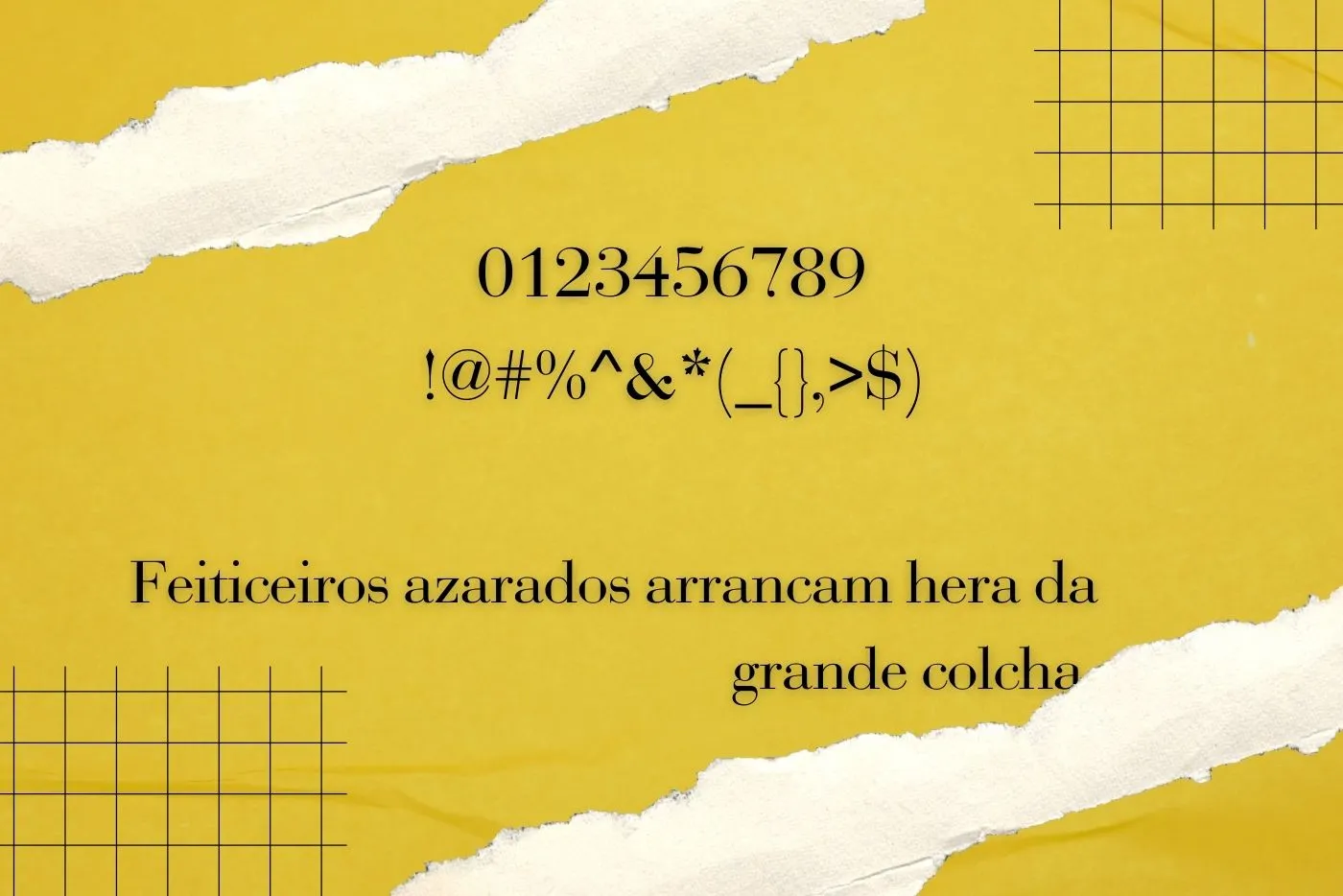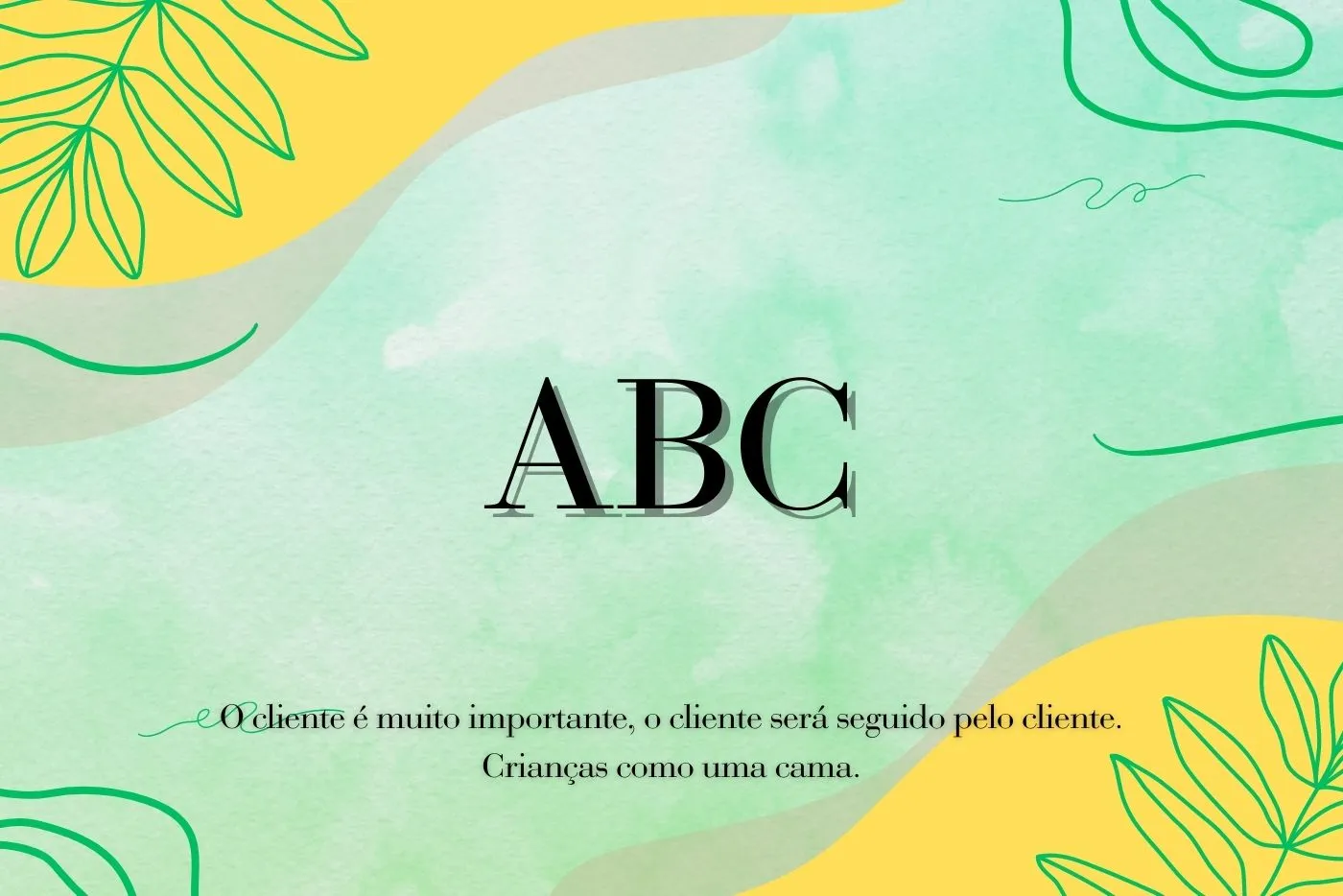
A fonte Bodoni é uma fonte serifada criada pelo designer italiano Giambattista Bodoni no final do século XVIII. A fonte é caracterizada por seu alto contraste entre linhas finas e grossas e suas serifas elegantes e nítidas.
Bodoni é amplamente considerado um dos designers de tipos mais importantes do século 18, e seu tipo de letra é frequentemente usado em design gráfico e impressão. Seu semelhante fonte liberty é muito clássico.
Bodoni criou vários estilos de sua fonte, incluindo Bodoni Antiqua, Bodoni Bold e Bodoni Ultra. Cada estilo tem suas próprias características únicas, como espessura do traço e espaçamento entre letras. Essa fonte é frequentemente usada em design editorial, especialmente para títulos e cabeçalhos. Você também pode verificar a ferramenta geradora deste tipo de letra para vários designs.
Você também pode verificar a ferramenta geradora online desta família de fontes. Essa fonte contém um grande número de caracteres e glifos, incluindo letras maiúsculas e minúsculas, números e sinais de pontuação. A fonte é frequentemente associada à elegância e sofisticação e é popular no design gráfico de luxo.
Fonte Bodoni História
A história desta fonte começa no final do século 18, quando o impressor e tipógrafo italiano Giambattista Bodoni a projetou. Bodoni foi um dos impressores mais célebres de sua época e é amplamente considerado um dos maiores tipógrafos de todos os tempos. Ele era conhecido por sua habilidade em criar tipos de letra elegantes e precisos, com proporções perfeitas e letras requintadas.
Bodoni desenhou a fonte que leva seu nome em 1798, depois de trabalhar por muitos anos como impressor em Parma, na Itália. Seu objetivo era criar uma fonte clara, precisa e elegante, com alto contraste entre traços grossos e finos e serifas nítidas e bem definidas.
Essa fonte tornou-se incrivelmente popular no início do século 19 e foi amplamente usada para design de livros, publicidade e outros materiais impressos. Sua popularidade continuou ao longo do século 20 e continua sendo uma fonte popular para design gráfico hoje. Nos últimos anos, os designers criaram muitas variações e adaptações da fonte Bodoni original, preservando seu estilo e elegância distintos.
Estrutura da Fonte Bodoni
Informação da Fonte
| Nome | Fonte Bodoni |
| Designer | Giambattista Bodoni |
| Estilo | Serifa |
Família de Fontes Bodoni
- Bodoni Antiqua
- Bodoni Bold
- Bodoni Ultra
Por Que Bodoni é uma boa Fonte?
Bodoni é considerada uma boa fonte por vários motivos.
Em primeiro lugar, é uma fonte serifada elegante e clara, com serifas bem definidas e alto contraste entre traços grossos e finos. Isso facilita a leitura, especialmente em tamanhos maiores, e confere uma aparência distinta e clássica, frequentemente associada ao luxo e à sofisticação.
Em segundo lugar, a fonte tem uma longa história de uso em tipografia e design gráfico, e sua popularidade dura mais de dois séculos. Isso significa que ele foi refinado e aprimorado ao longo do tempo e comprovou sua eficácia e versatilidade em uma ampla gama de aplicações.
Por fim, Bodoni é uma fonte que oferece muitas variações e adaptações, desde estilos arrojados e condensados até designs mais delicados e ornamentados. Isso permite que os designers personalizem a fonte para atender às suas necessidades específicas e criar designs únicos e memoráveis.
Perguntas Frequentes!
Quem criou a Fonte Bodoni e quando foi desenvolvida?
Foi criado pelo designer de tipos italiano Giambattista Bodoni no final do século XVIII.
Quais são as características distintivas da Fonte Bodoni?
É conhecida por seu design elegante e atemporal, caracterizado pelo alto contraste entre traços grossos e finos.
Posso usar a Fonte Bodoni para cabeçalhos e corpo do texto?
Sim, é comumente usado para cabeçalhos e corpo de texto, especialmente em designs clássicos e sofisticados.
Existem exemplos notáveis de projetos ou publicações que usam a Fonte Bodoni?
Muitas publicações e designs conhecidos, como capas de livros e layouts editoriais, o utilizaram por sua estética elegante e refinada.